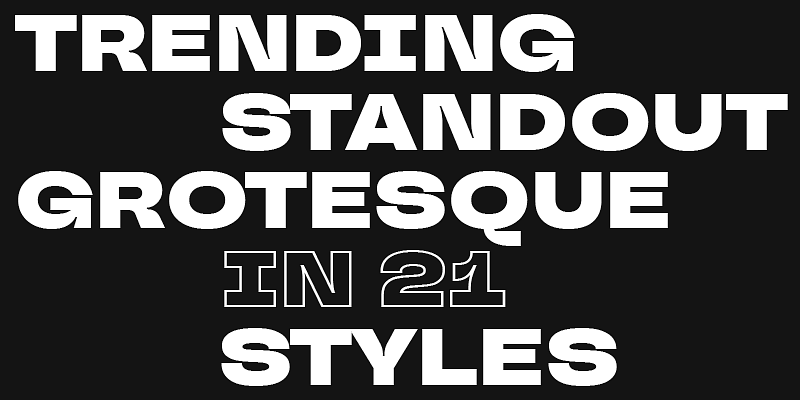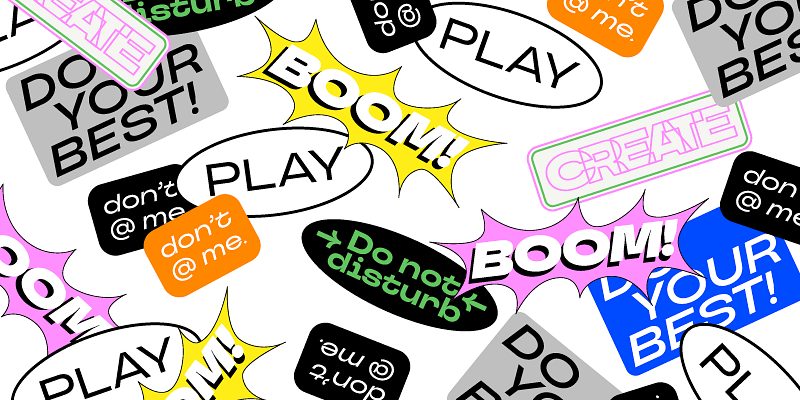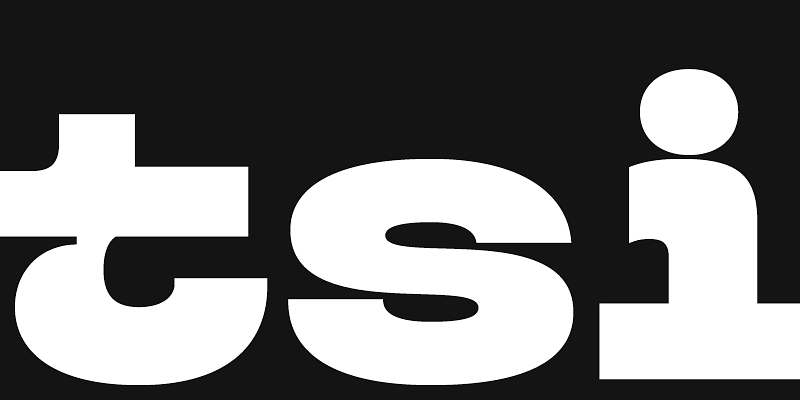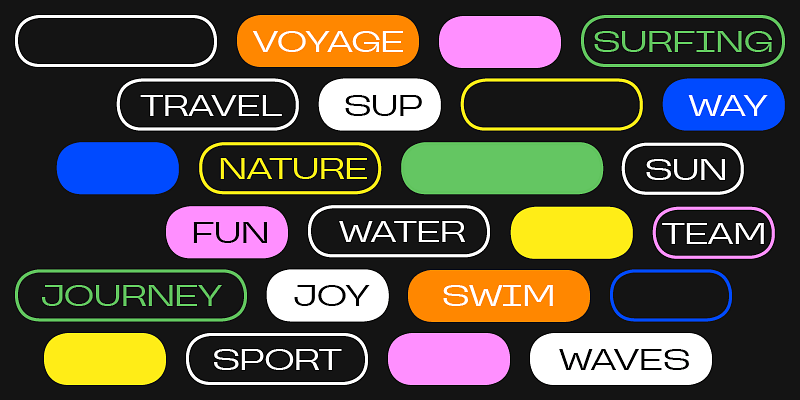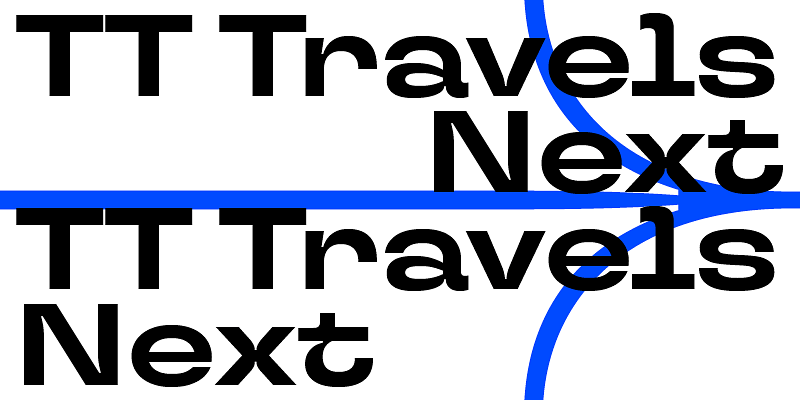
TT Travels Next 書体のアイデアは、印刷物でも web でも、様々なセットで使用できる、非常にトレンディでモダンなワイドディスプレイ サンセリフを作成することでした。この書体は非常に幅の広いプロポーションを持ち、太いスタイルから明るいスタイルに移行しても文字がほとんど狭くなりません。TT Travels Next は、誇張された閉じた絞り、低コントラスト、目立つ視覚補正、およびソフトな形状とシャープな形状の調和のとれた組み合わせを備えています。